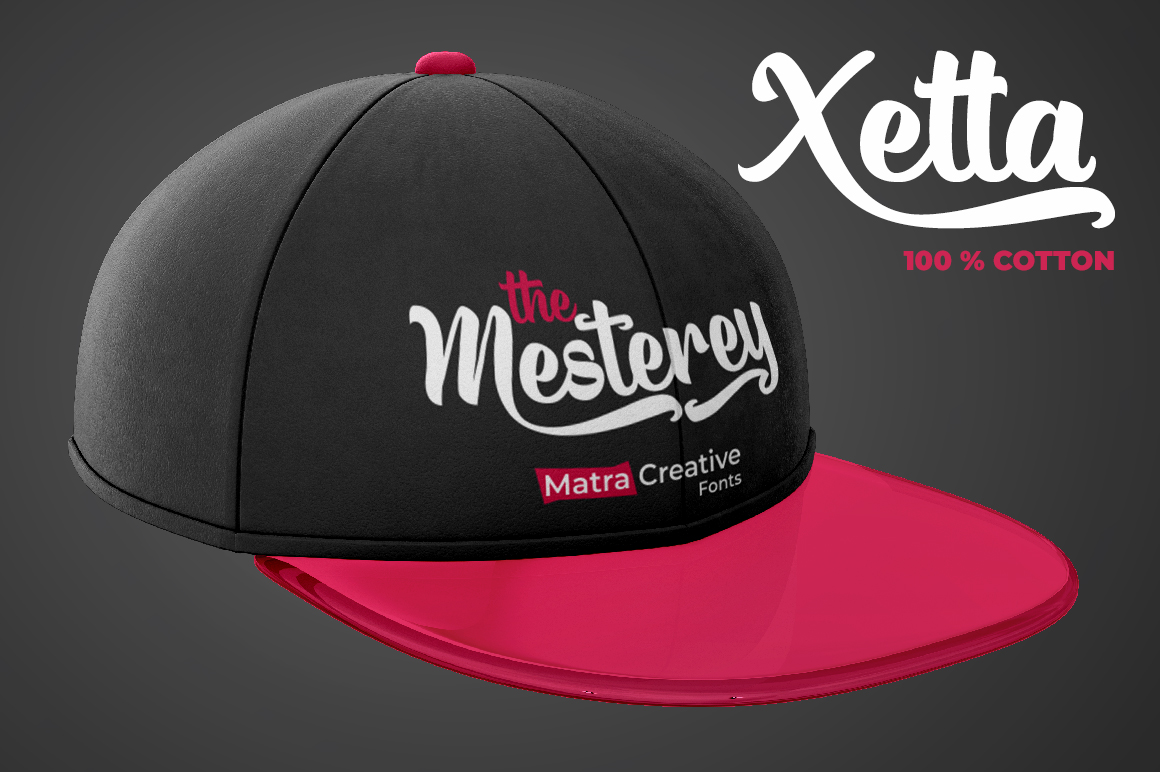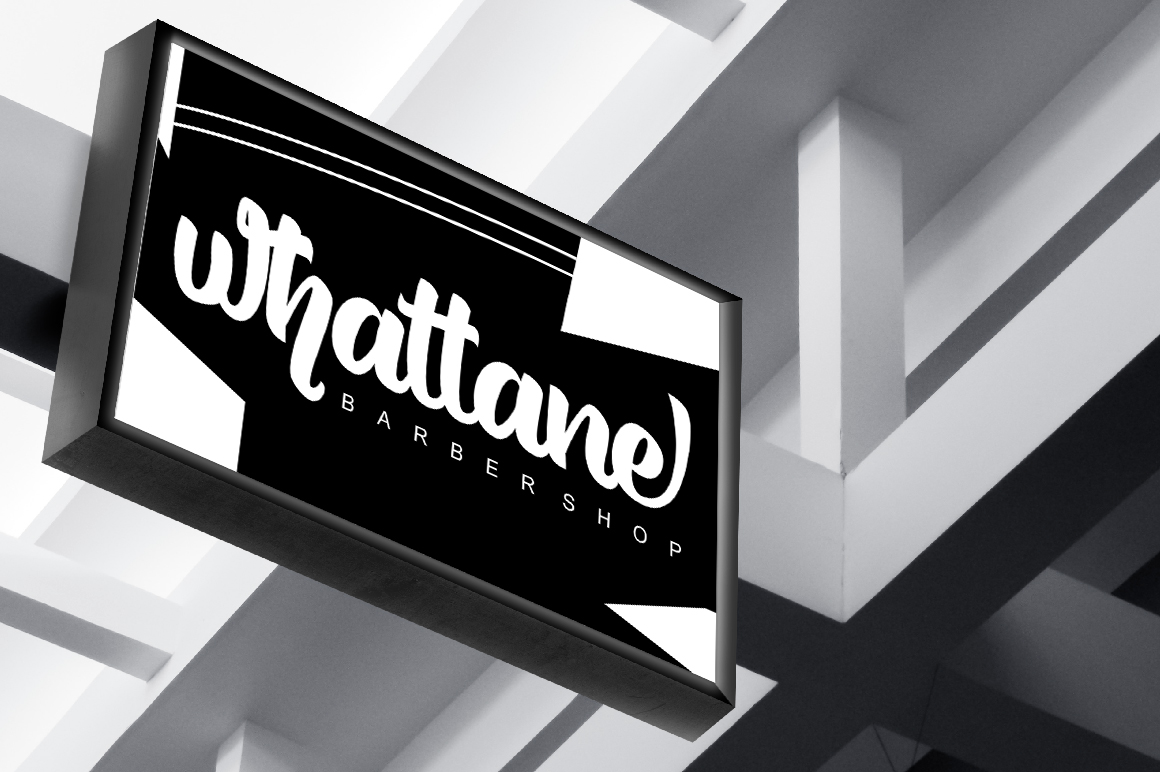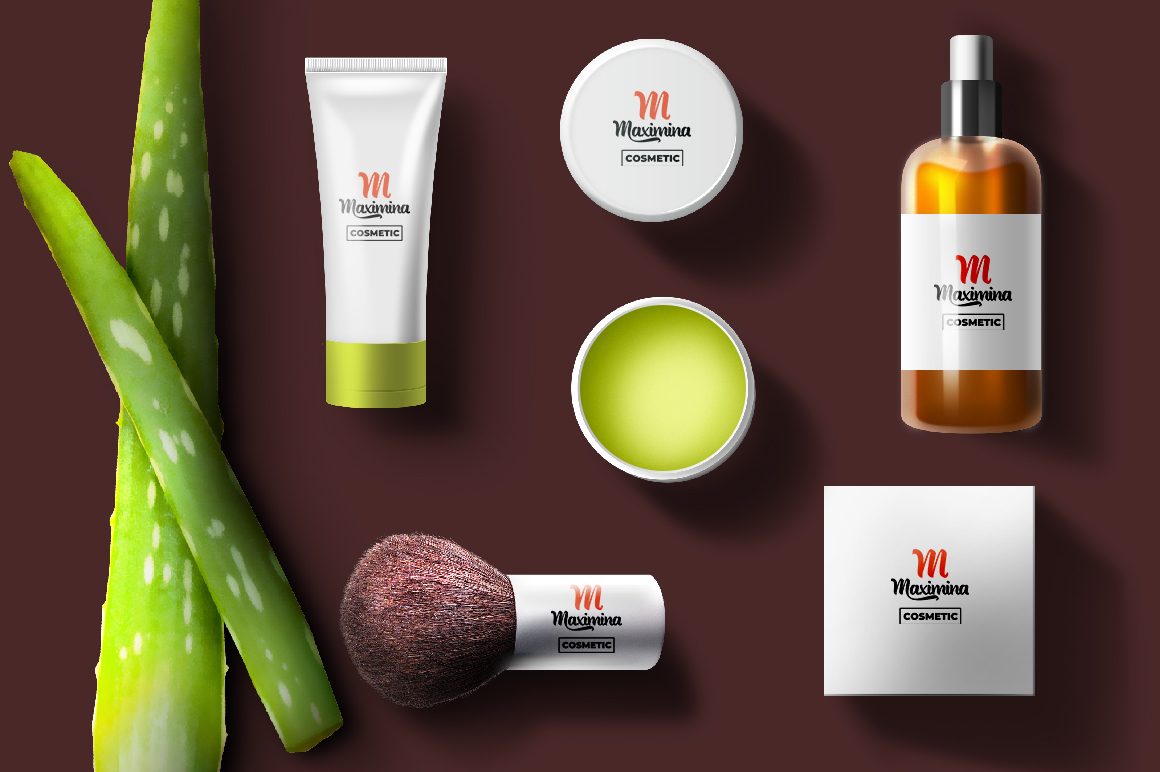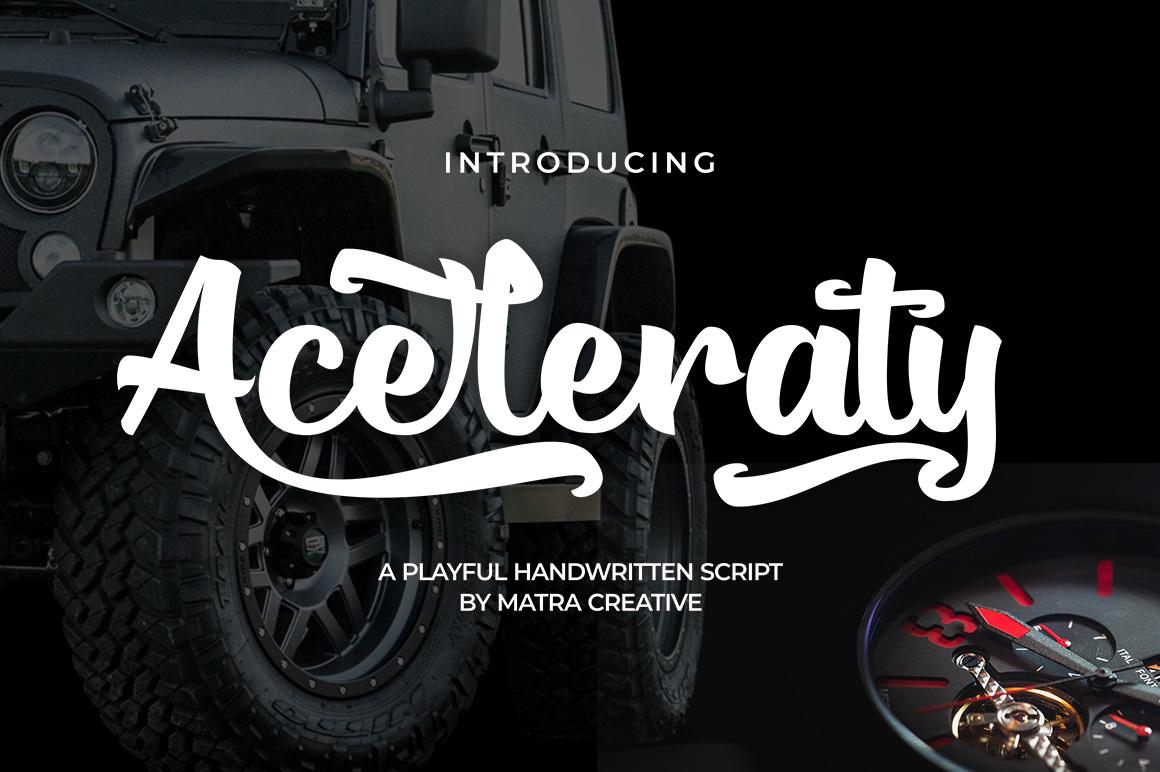
Aceleraty Script Font
Aceleraty – Font Tulisan Tangan adalah font skrip kuas berdasarkan ekspresi tulisan tangan asli, memungkinkan Anda mengubah jenis menjadi karya yang menarik dan indah. Tampilan tulisan tangan menambahkan sentuhan manusia nyata pada berbagai hal dan dilengkapi dengan banyak detail yang penuh cinta.
Aceleraty- Handwritten Font memiliki banyak alternatif yang memberi Anda kemungkinan untuk membangun teks Anda hampir seperti tulisan tangan dengan semua ketidaksempurnaan dan variasi menawan yang dimiliki tulisan tangan yang sebenarnya. Aceleraty akan bekerja dengan sempurna untuk fashion, merek e-commerce, blog tren, butik pernikahan, atau bisnis apa pun yang ingin tampil mewah dan chic.